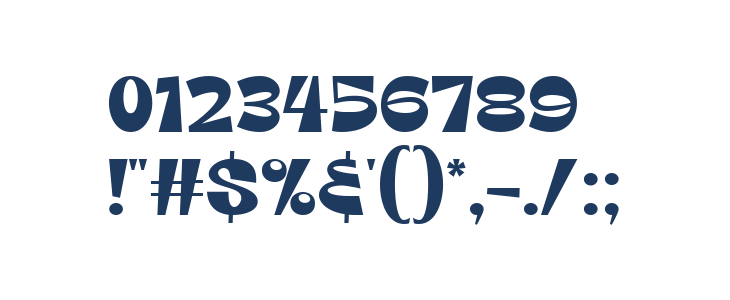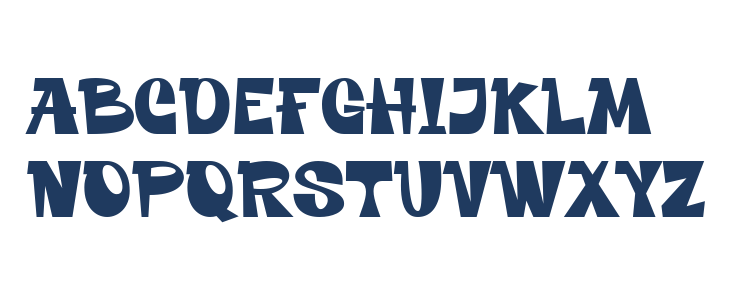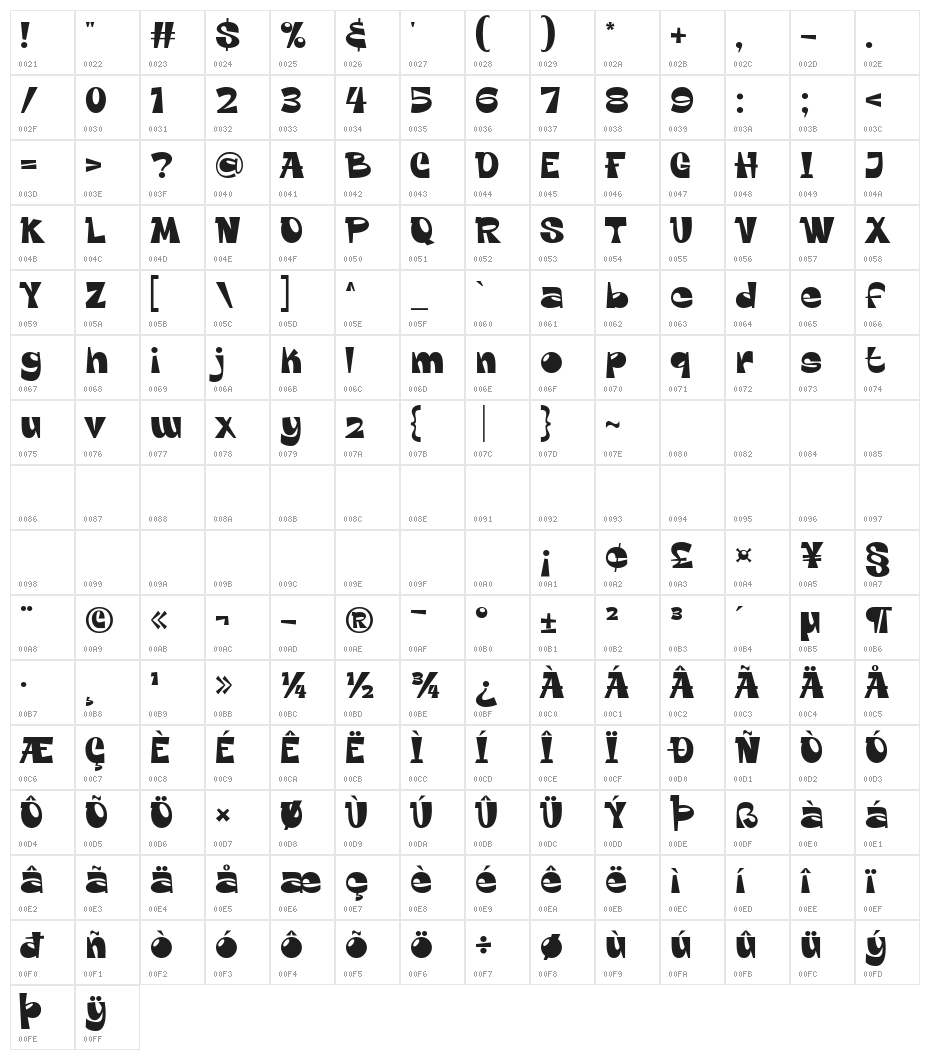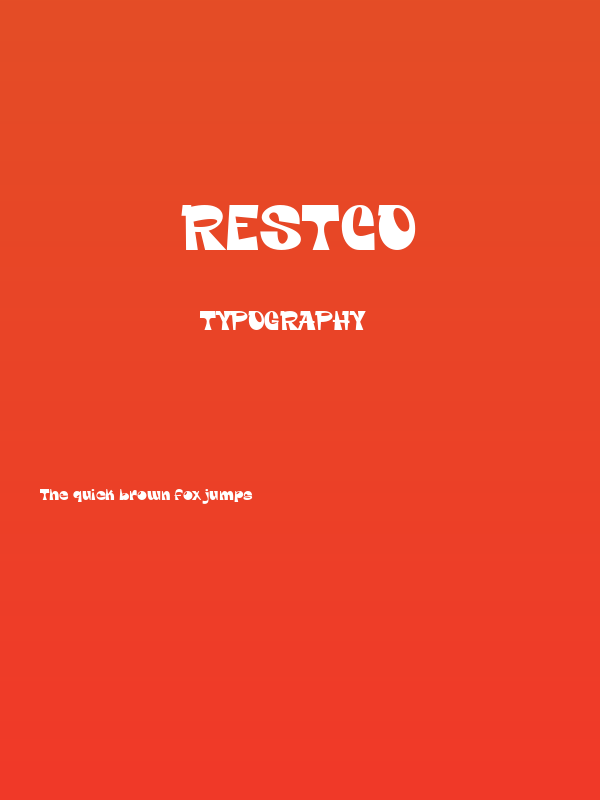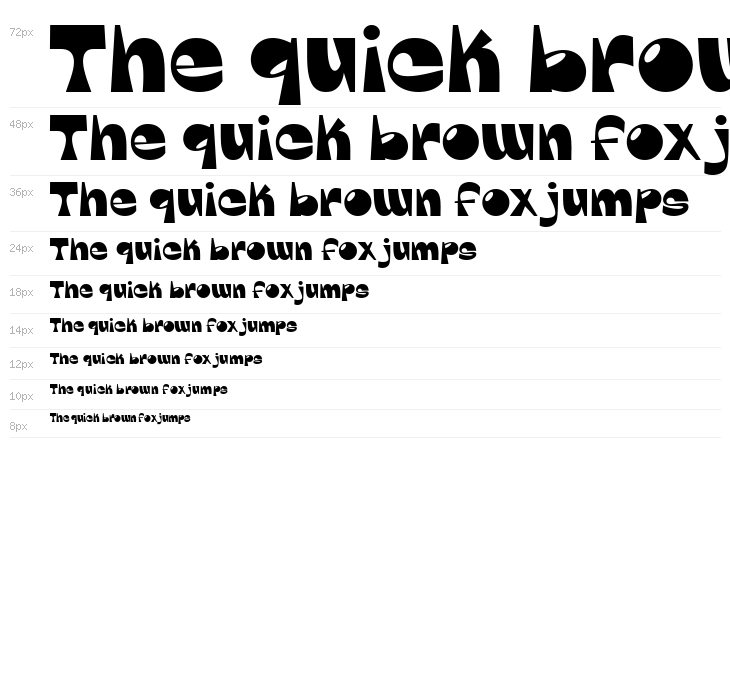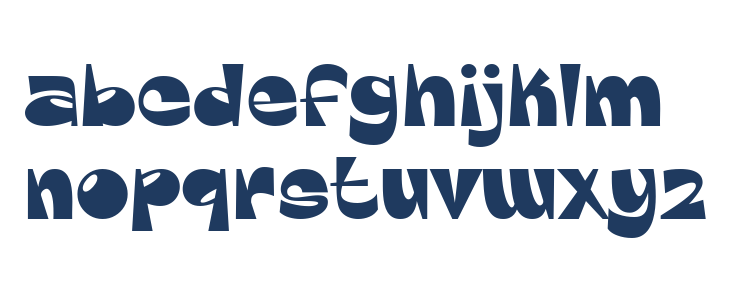
Restco Font
✎ bubble letter
| Categorie | bubble letter |
| Stile generale | Playful, Decorative, Modern |
| Caso d'uso | Headlines, Posters, Logos, Event Materials |
| Progetti proposti | Children's books, posters, party invitations, branding for playful products, event flyers. |